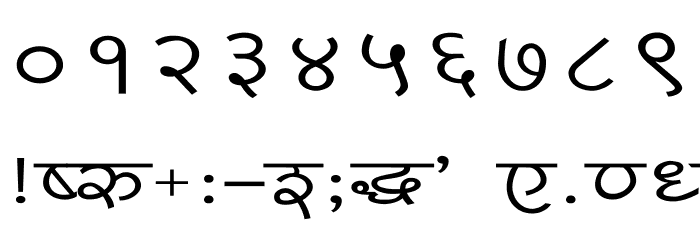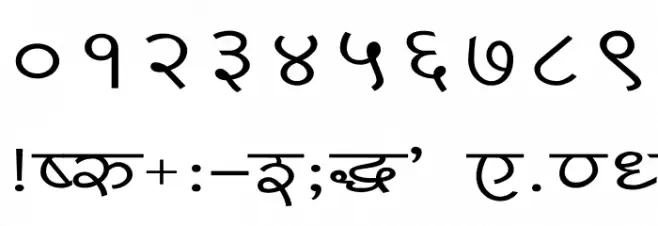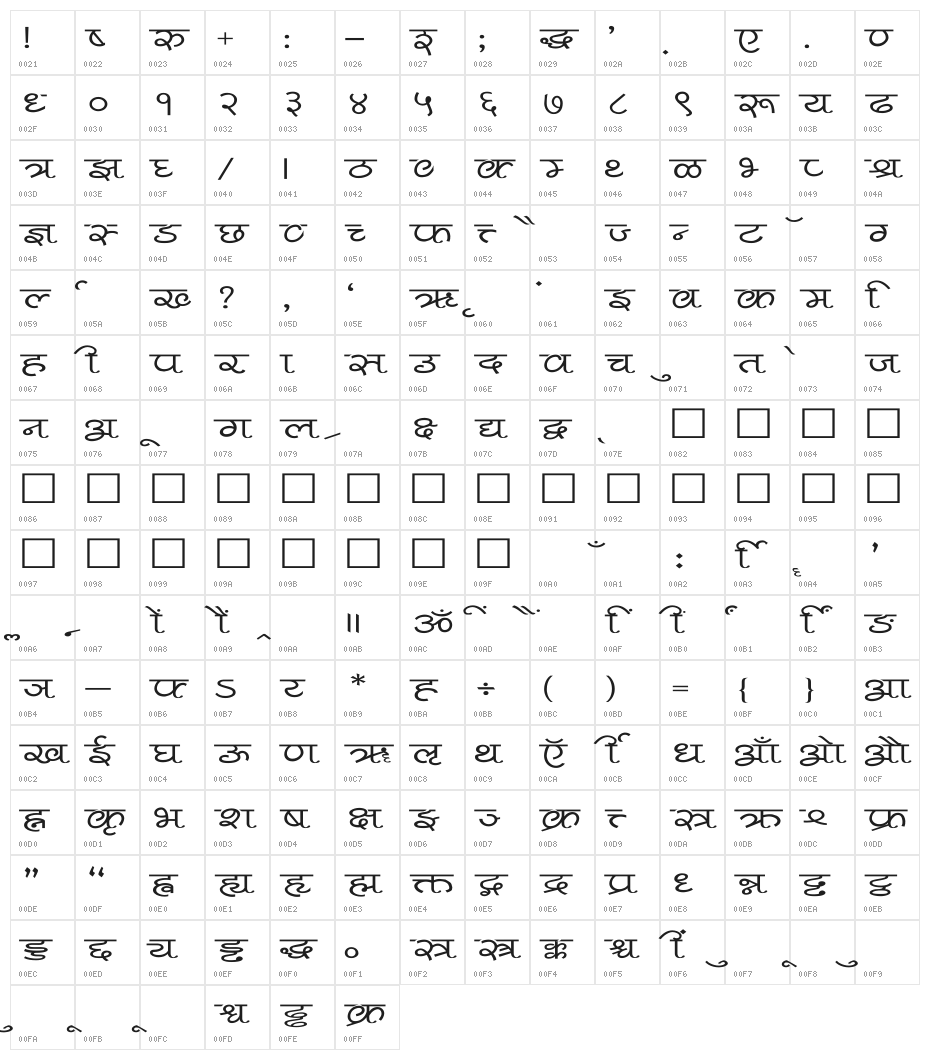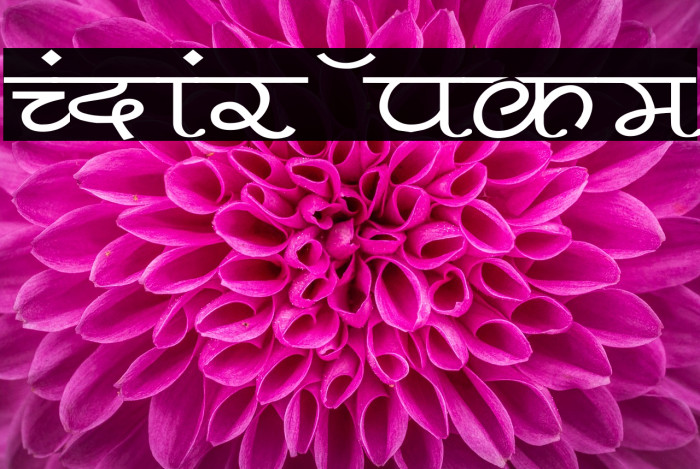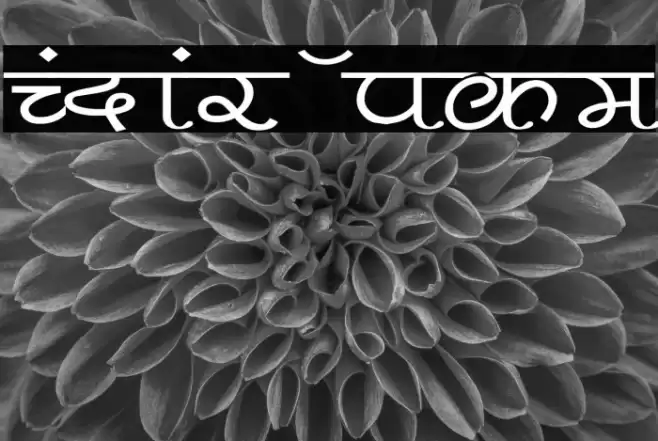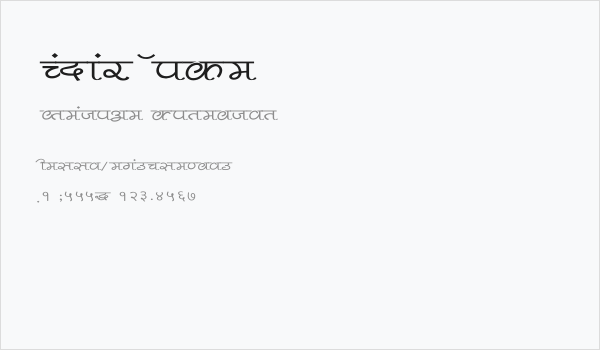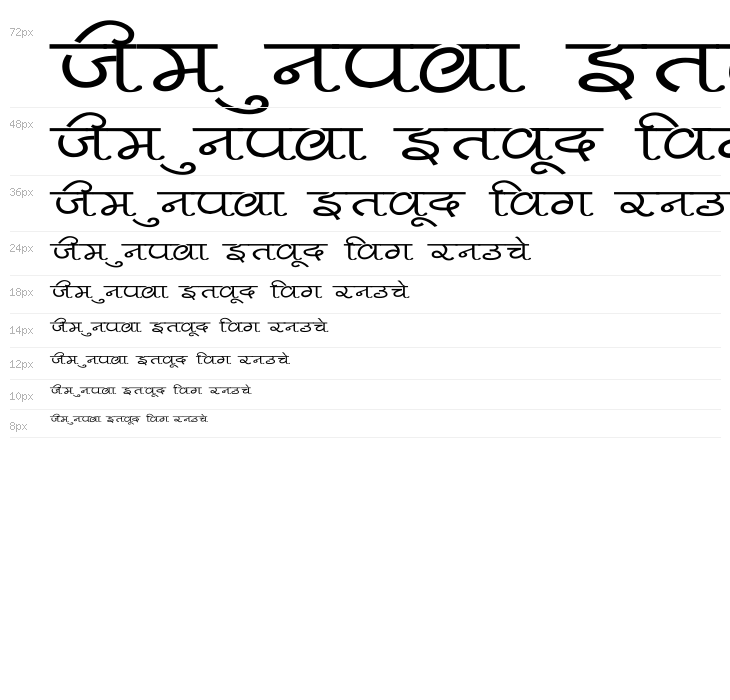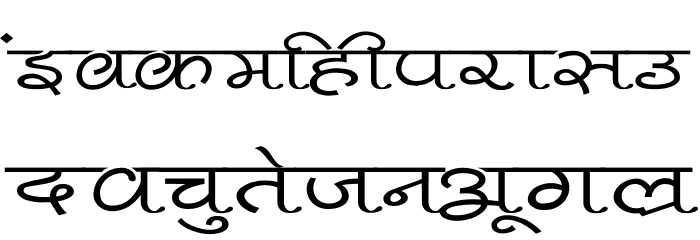
Pankaj Wide Font
✎ Calligraphic
| Categorias | Calligraphic |
| Estilo geral | Traditional, Decorative |
| Caso de uso | Logos, Invitations, Artistic designs |
| Projetos propostos | Ideal for cultural projects, invitations, artistic designs, and branding that requires a traditional touch. |